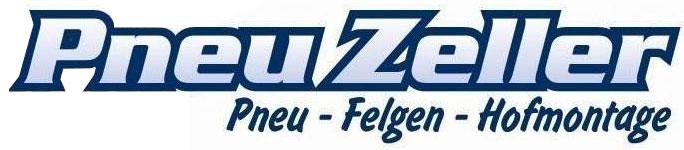
Pneu Zeller Aarberg
ich Suche nach diesen Schriftarten.
Es handelt sich um ein Firmenlogo, welches wir um zusätzliche Buchstaben (Pneu Zeller AG) erweitern möchten. Der Ersteller ist leider nicht bekannt. Die Firma ist in der Schweiz, wechselt und verkauft Pneus.
Gelöst von Hans Schumacher
Die Basis von »Pneu Zeller« ist wahrscheinlich eine Serpentine, gibt es in unterschiedlichen Versionen diverser Hersteller, die URW-Fassung scheint recht nahezukommen. https://www.myfonts.com/fonts/urw/serpentine/d-bold-italic/
PS: »Pneu-Felgen-Hofmontage«, Schriftart nennt sich Flash, ist ein wenig elektronisch zusammengestaucht. https://www.myfonts.com/fonts/lanston/ltc-flash/